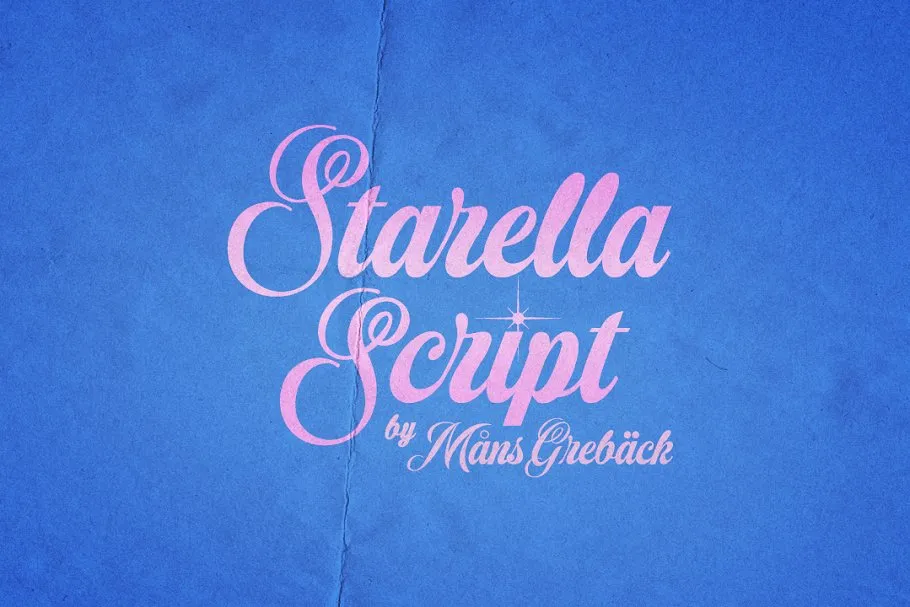
Olá a todos! Estou aqui um belo adorno para suas criações digitais com Starella Script Font. Criada pelo Designer Mans Greback, essa fonte script é ideal tanto para as mais majestosas logotipia quanto para gráficos memoráveis e criativos. Estrelada com letras alternativas e de swash, permite-lhe uma maior flexibilidade nas criações. Para criar um swash específico, basta adicionar um sublinhado no início ou fim da letra desejada. Por exemplo, transformar a S em S_tarella para obter uma versão especializada desta notável fonte. A Starella Script é perfeita para aqueles que procuram um toque elegante e único em suas criações. Seja para design gráfico, branding ou qualquer tipo de projeto digitais, essa fonte é uma escolha impecável para adicionar a sua personalidade e sofisticação. Descubra agora Starella Script Font e dê vida à sua próxima criação!